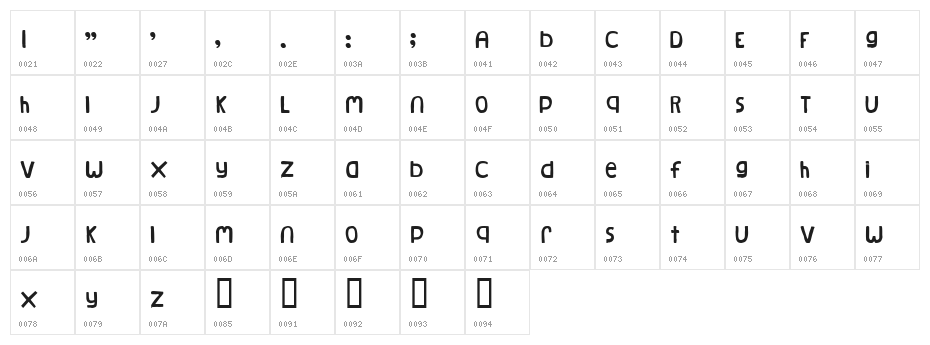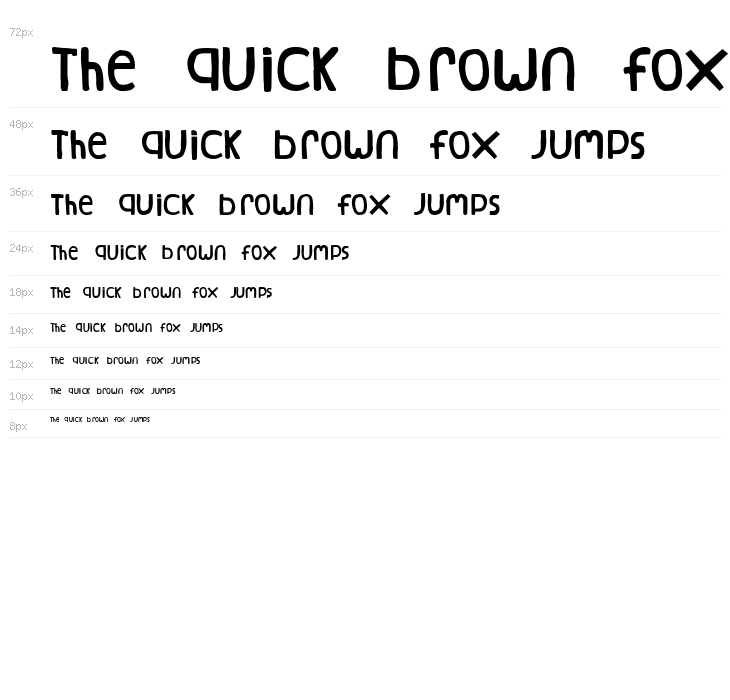
Natural Log Font
| Caso d'uso | Headlines, Logos, Informal Text |
| Progetti proposti | Ideal for children's books, casual branding, greeting cards, and creative posters. |